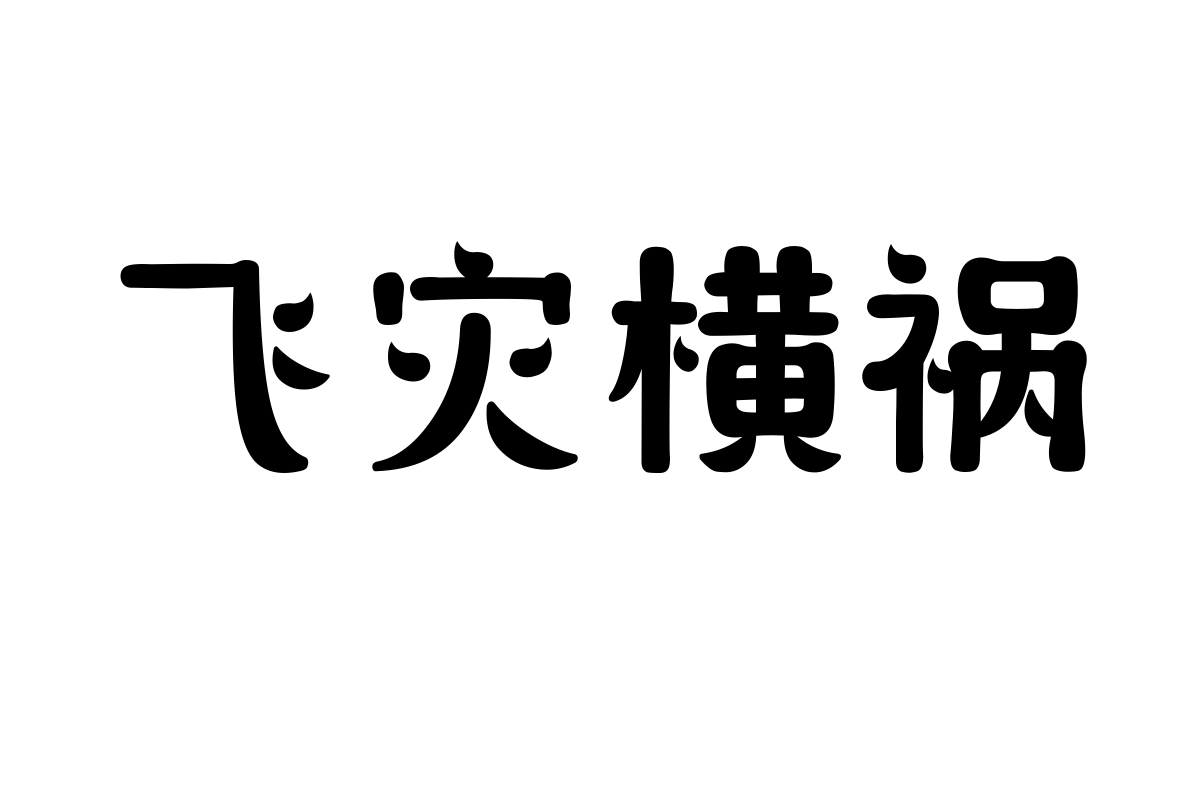
造字工房清奈体是一套由造字工房设计团队开发的中文字体。这套字体以其独特的风格和美观的字形受到了广大设计师和用户的欢迎。
清奈体的特点在于其简洁而优雅的线条,以及流畅的字形过渡。它的笔画粗细适中,既不会过于粗犷,也不会过于细薄,使得整体视觉效果更加和谐统一。此外,清奈体的字形结构紧凑,但不失灵动,给人一种清新脱俗的感觉。
在设计上,清奈体注重实用性和美观性的结合。无论是用于标题、正文还是装饰性文字,它都能展现出良好的视觉效果。同时,清奈体也考虑到了不同场景的应用需求,如网页设计、海报设计、书籍装帧等,都能找到合适的应用场景。
总的来说,造字工房清奈体是一款具有较高艺术价值和实用价值的中文字体。它不仅能够满足设计师们对于字体的审美追求,还能为各类设计作品增添一份独特的魅力。